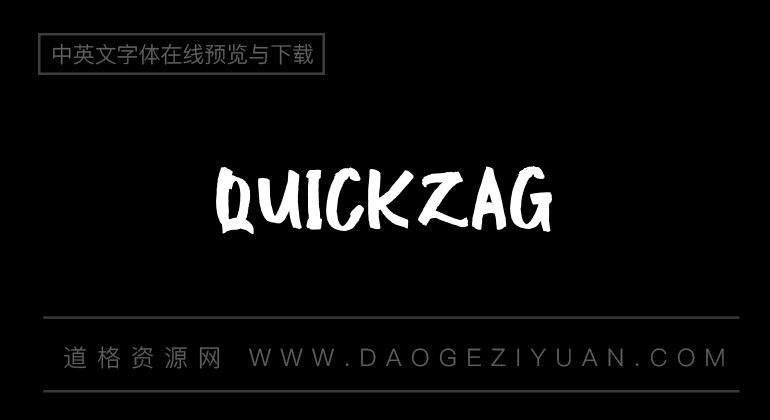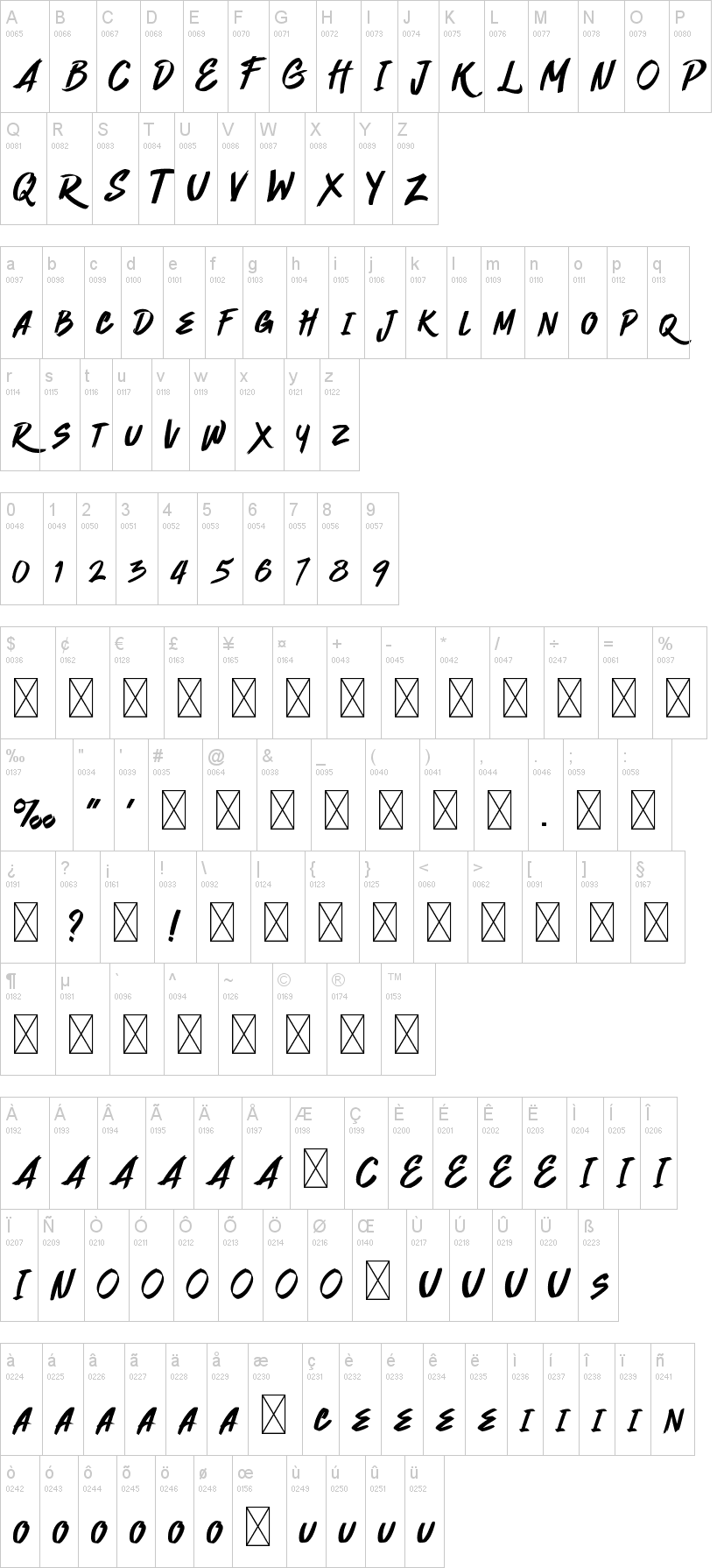
Quickzag 字体是一款简约、灵活的字体,由著名设计师Paula Nazal设计。它拥有清晰的线条,让文本更加易读。它的字体设计简单,但又不失灵活性,可以用在各种印刷和设计项目上。Quickzag 字体具有极佳的空间感,可以让文本更加精细,而且可以调整字体大小,以适应不同的设计需求。内容介绍
Quickzag是一款非常不错的手写艺术字体,具有很好的视觉感,适合于文化类的宣传设计、商业类品牌的广告和产品包装设计以及个性化文字排版等较多场景。